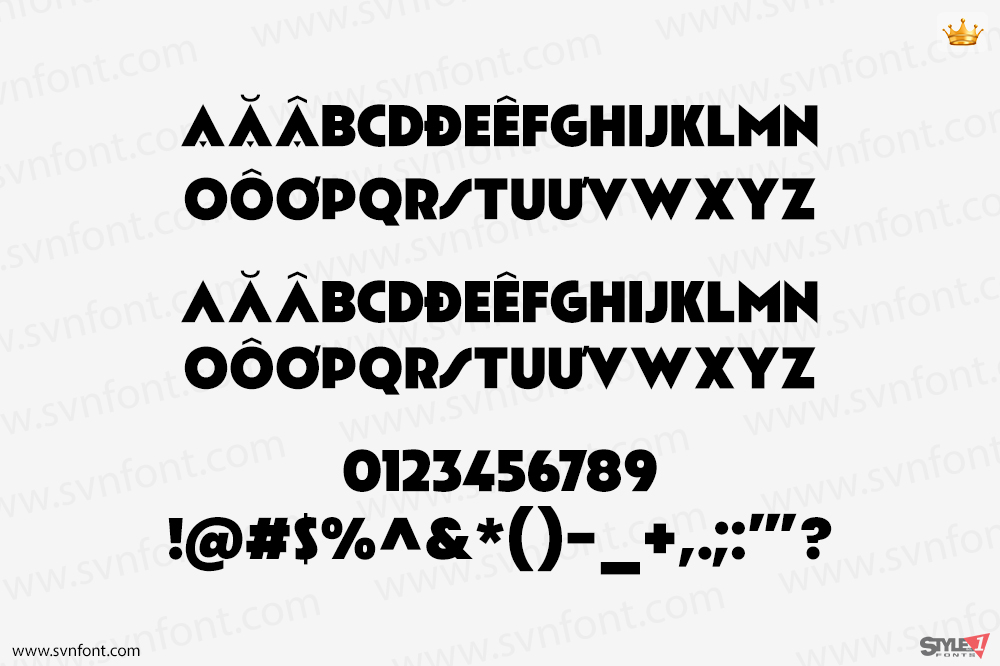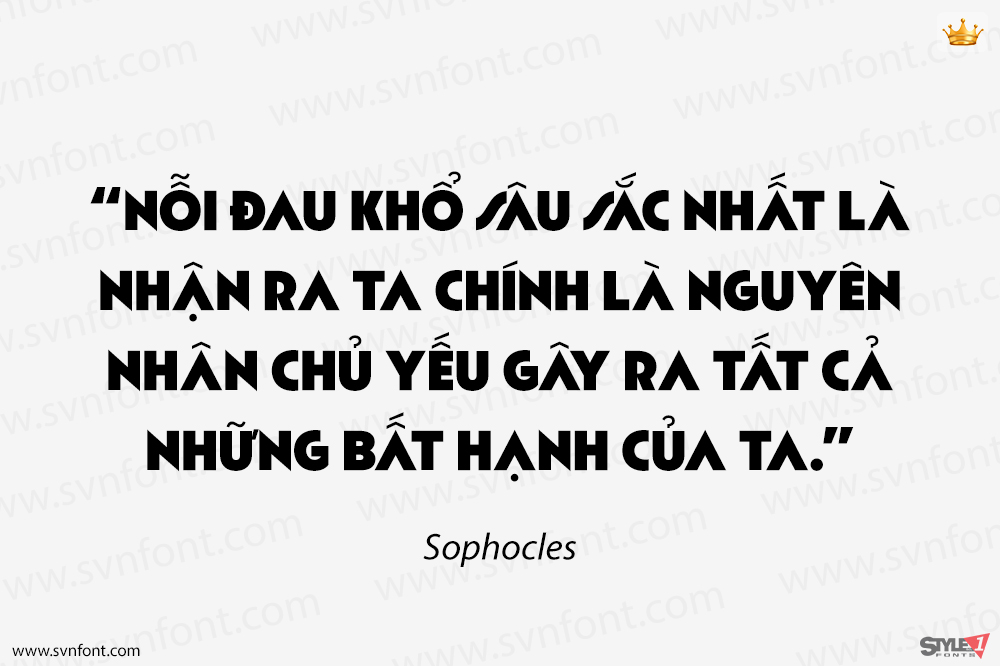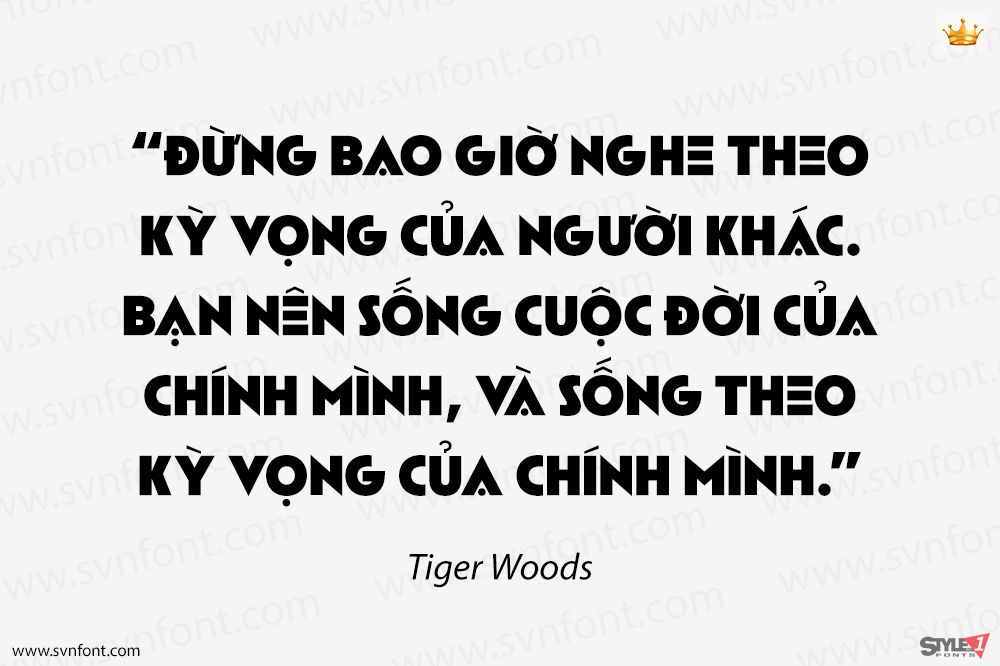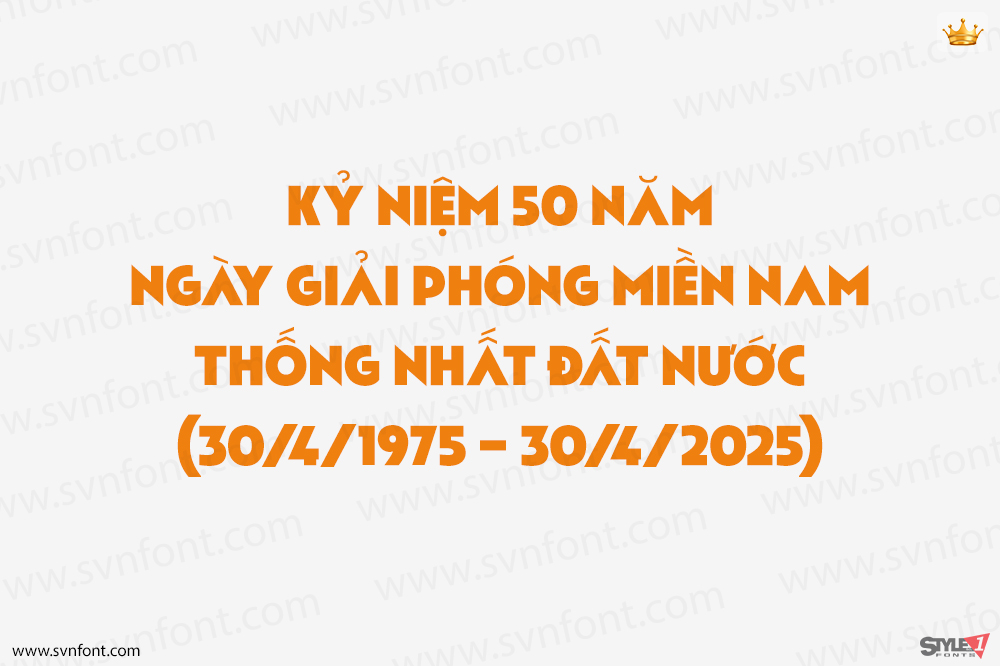
Apres Ski là một phông chữ hiển thị đậm chất retro sẽ đưa bạn quay ngược thời gian. Phông chữ này hoàn hảo cho bất kỳ dự án nào cần một chút quyến rũ cổ điển. Với 266 chữ ghép, nó đủ linh hoạt để được sử dụng trong nhiều ứng dụng thiết kế khác nhau.
Những đường nét mạnh mẽ, đậm của Apres Ski khiến nó trở thành một lựa chọn lý tưởng cho các tiêu đề và các thiết kế bắt mắt khác. Nó hoàn hảo để thêm một nét retro vào thương hiệu của bạn, hoặc để tạo ra các áp phích và đồ họa khác đòi hỏi sự chú ý…
Nhà thiết kế: Pixel Surplus
Nhà phát hành: Pixel Surplus